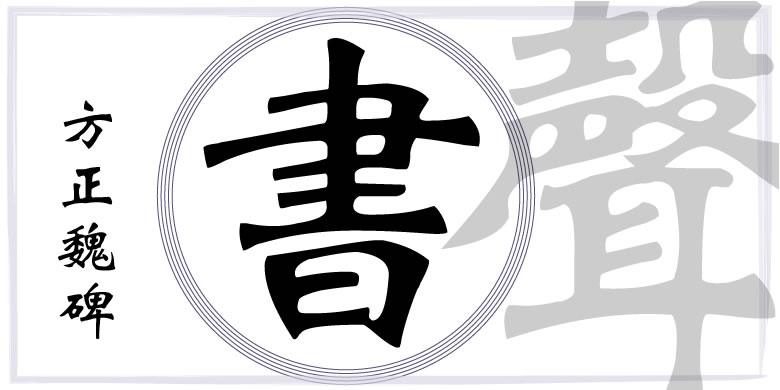
字体介绍 品牌:方正字库设计师:韩飞青发行时间:1996字库编码:大陆简体(GB2312-80)、大陆繁体(GB12345-90)、简繁扩展(GBK)、港台地区(BIG-5)分类:常规书写·毛笔 英文名称:.TTF 魏碑体是北魏时期产生的一种介于汉晋隶书和唐楷之间的新书体,又称为龙门体。方正魏碑的字形结构跌宕起伏,笔意朴拙,不避锋芒,规则中正。其风格苍劲坚实,适用于文化类的宣传设计,以及商业类品牌的广告和产品包装设计。 字体下载 官方下载